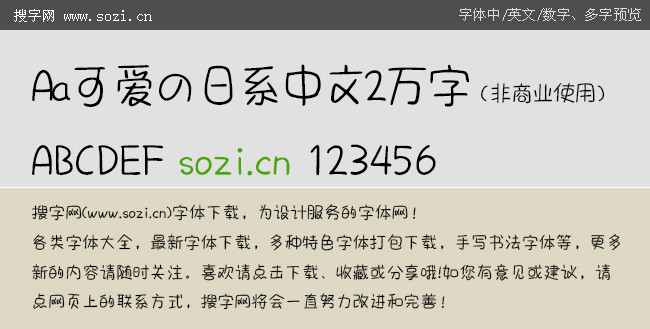
Aa可愛の日系中文2萬字
搜字網(wǎng)給大家提供一款A(yù)a可愛の日系中文2萬字(非商業(yè)使用)中文字體下載,該字體是一款可愛的藝術(shù)字體字體筆觸適中,字形圓潤可愛,具有很好的視覺感。適合書裝設(shè)計(jì)、包裝設(shè)計(jì)、海報(bào)設(shè)計(jì)等應(yīng)用(此字體為個(gè)人非商用版,商用可以聯(lián)系QQ:1006760504)。